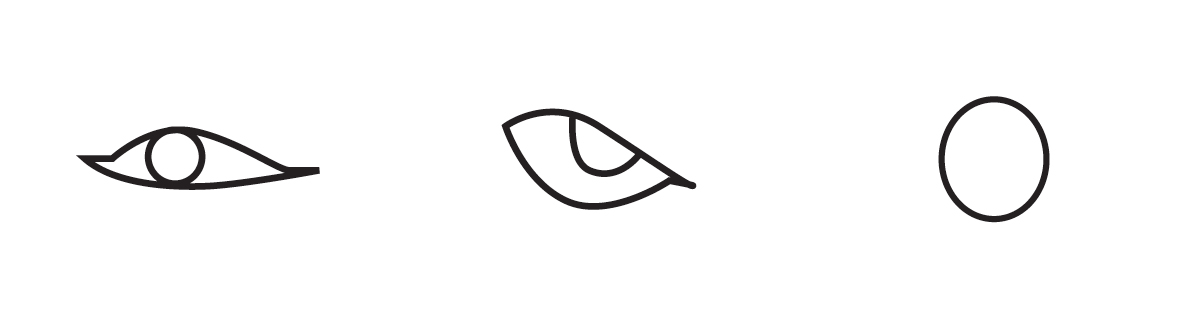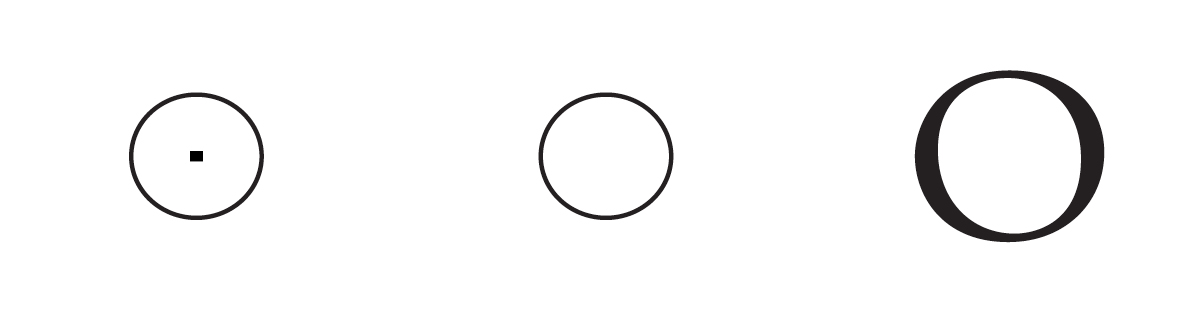
| Jeroglífico 3000 aC • Sinaítico 1600 aC • Etrusco 800 aC |
| Griego antiguo 800 aC • Latín antiguo 700 aC • Romano 100 aC |
Decimoctava letra del abecedario español y decimoquinta del orden latino internacional.
Su forma deriva del pictograma que representaba al ojo en los jeroglíficos egipcios.
Viene de la letra semita ayin, que era una consonante y de la griega omicron. Gracias a su extrema sencillez ha variado muy poco a lo largo del tiempo.
La minúscula y la mayúscula comparten forma general, aunque pueden tener sutiles distinciones.
| Capitular lombarda del siglo XV. Francia |
Alfabeto Lapidare Monster, diseñado por J. Midolle. Francia |
Brush script diseñada por Robert Smith en 1942
Mistral diseñada por Roger Excoffon para la fundidora Olive en 1953
| Futura |
Alfabeto ornamental del Siglo XIX |
| Buenos Aires tipográfico, trabajo de estudiante Javier Choi. 2015 |
Manual de tipografía del Reino Unido. 1900 |
Buenos Aires tipográfico, trabajo de estudiante de Tipografía 3, González, 2015.
Cooperplate Gothic, diseño original de Goudy. 1901
| "La letra O" Shigeo Fukuda, 1993 |
Mosaico, fotografiado por DG Sofía Chouza. 2015